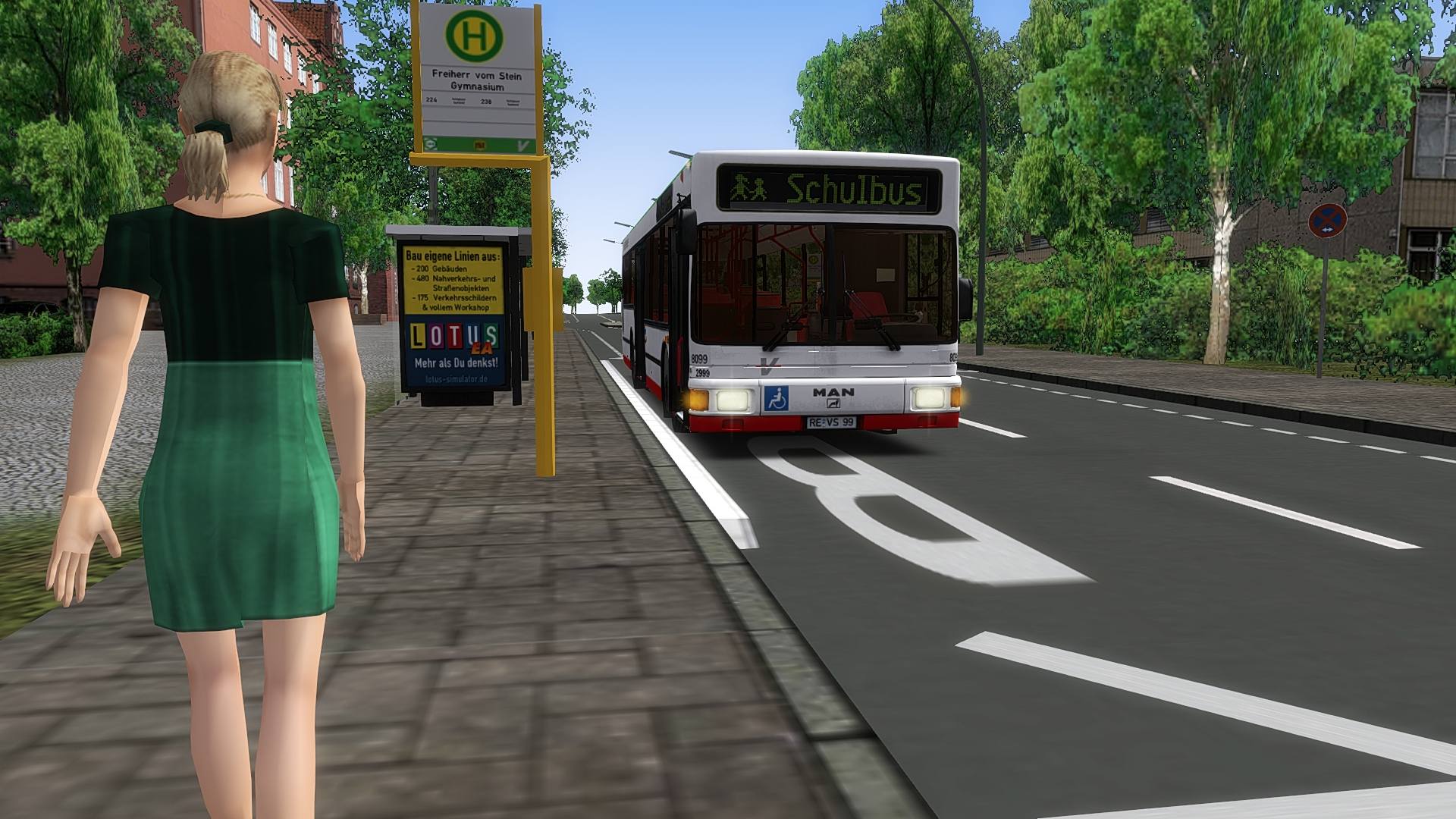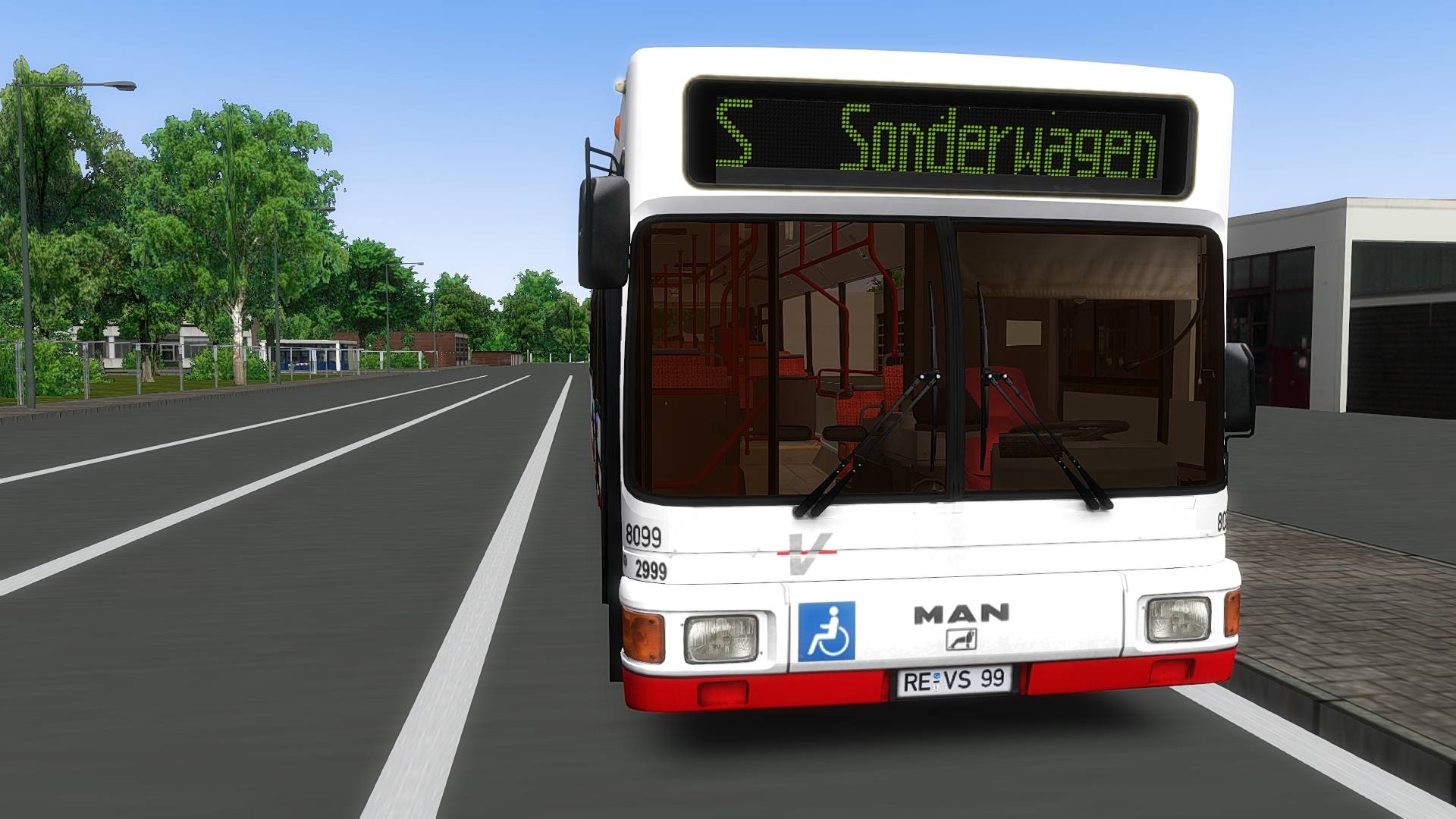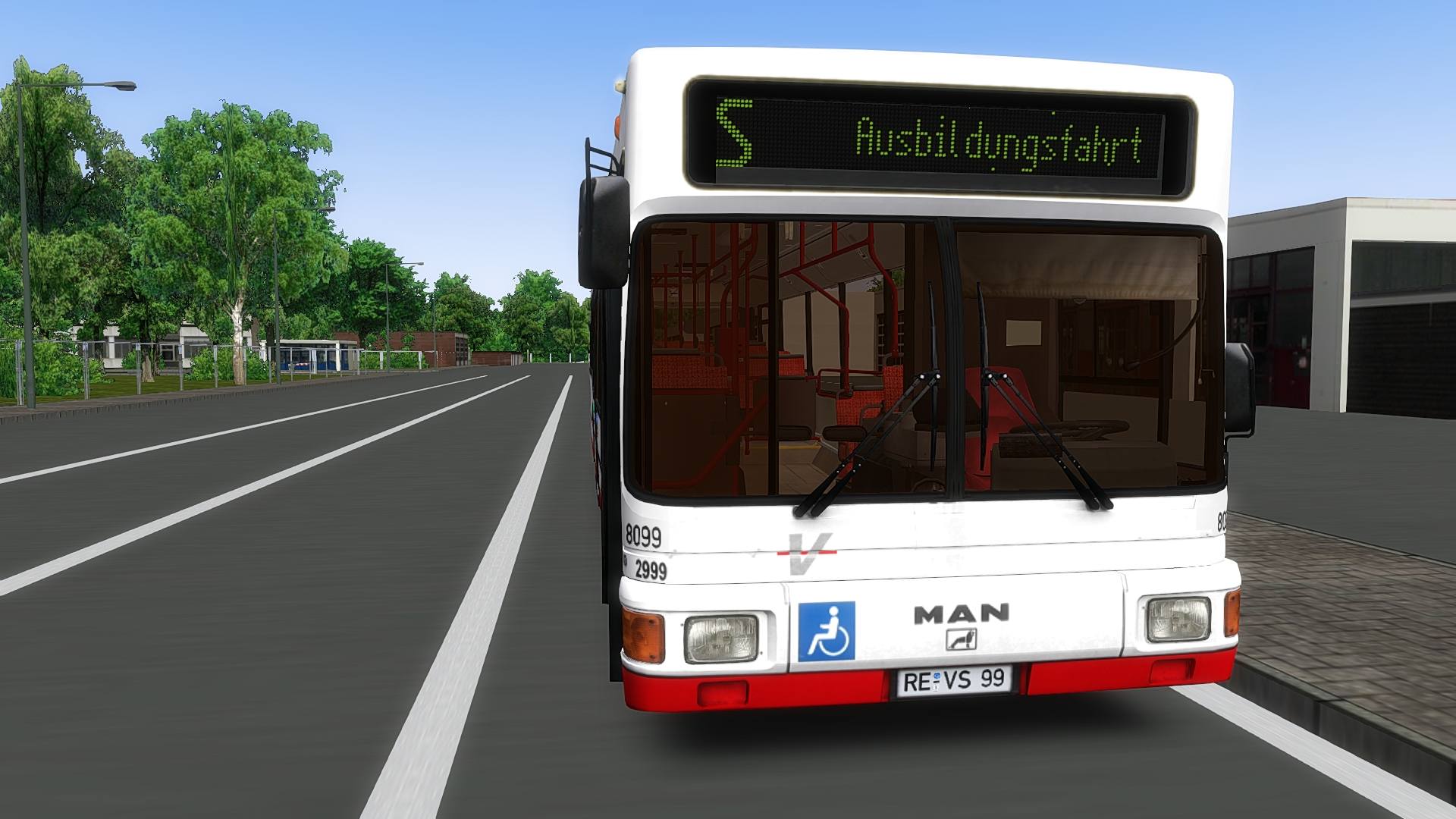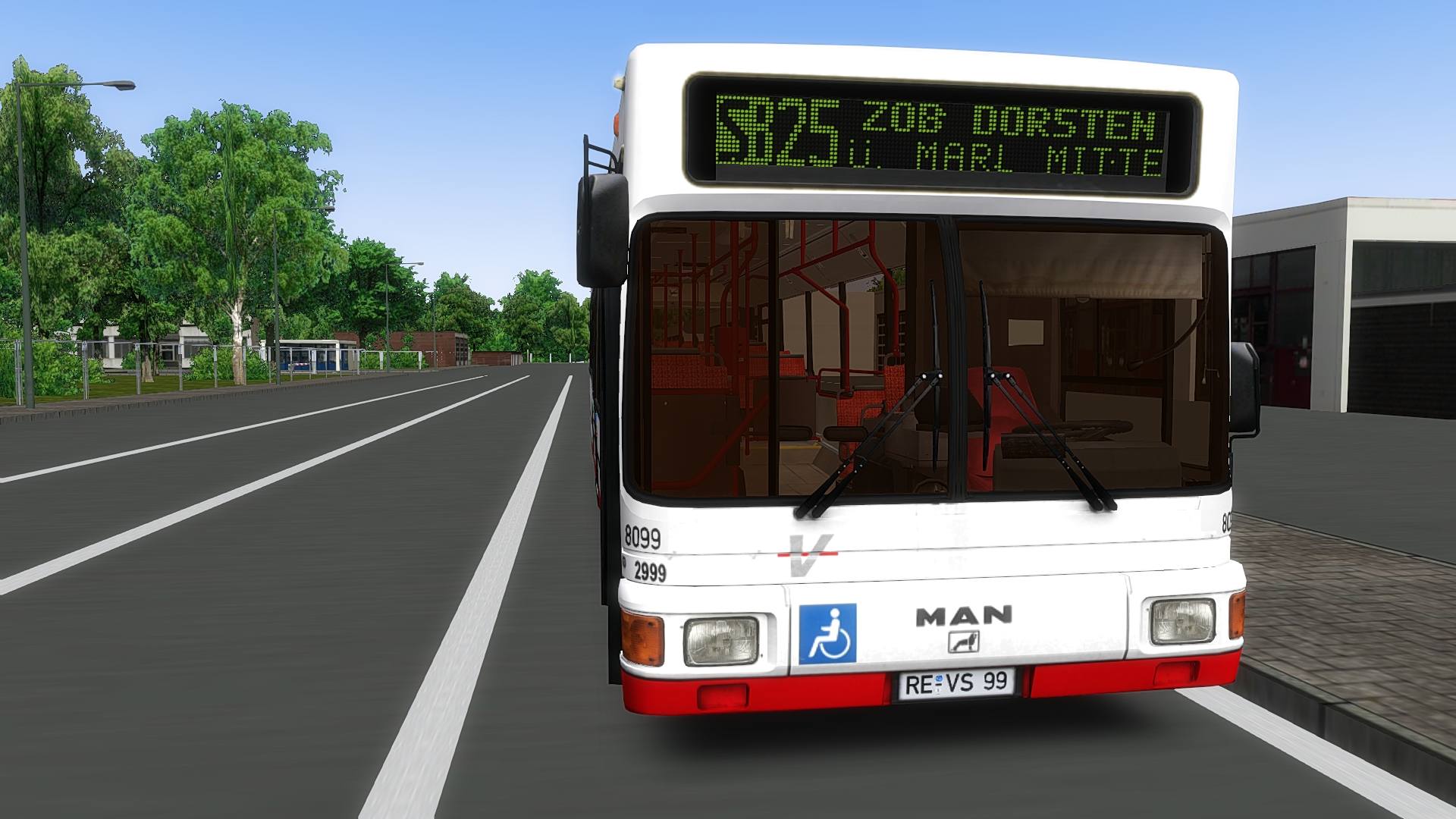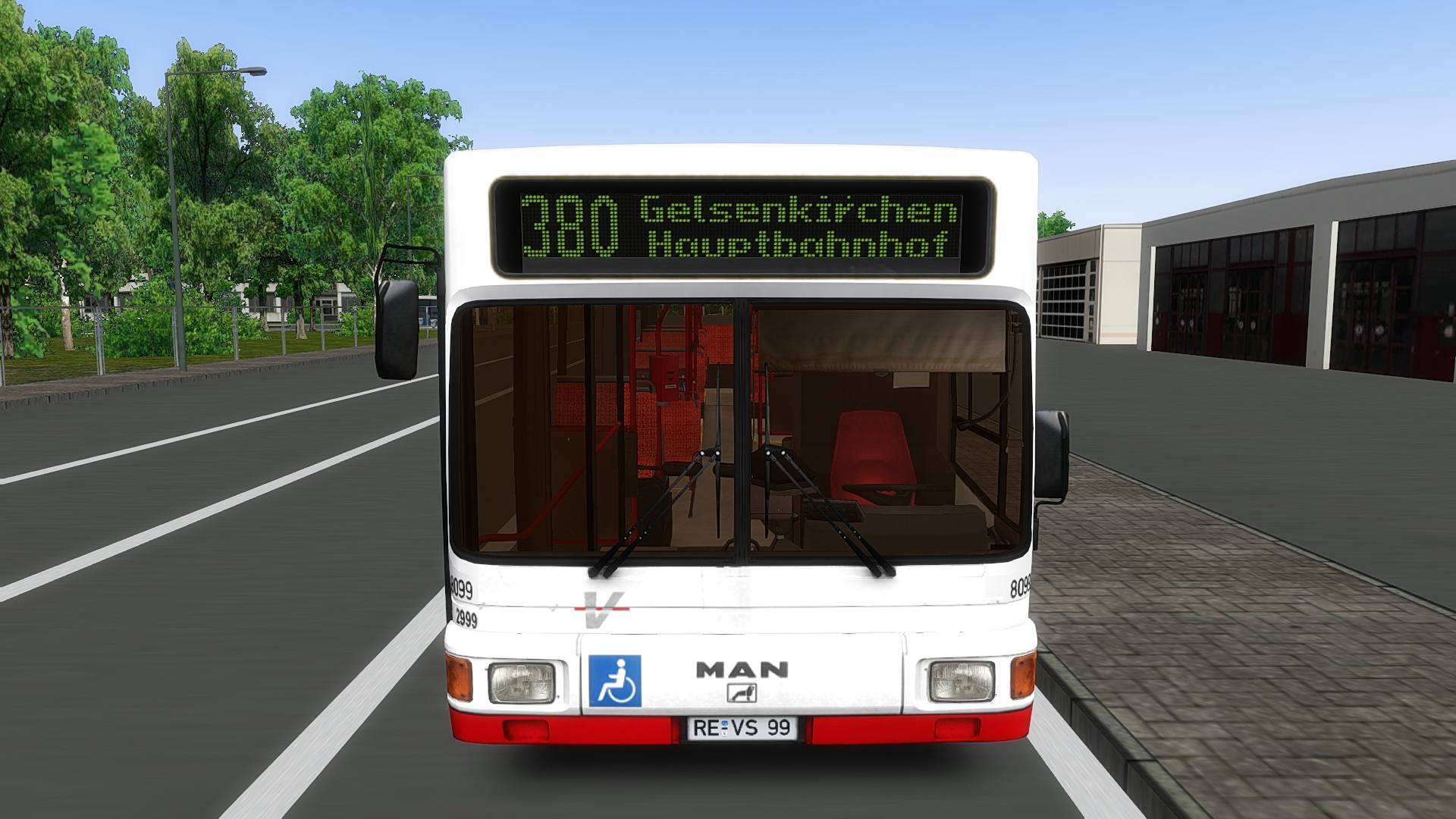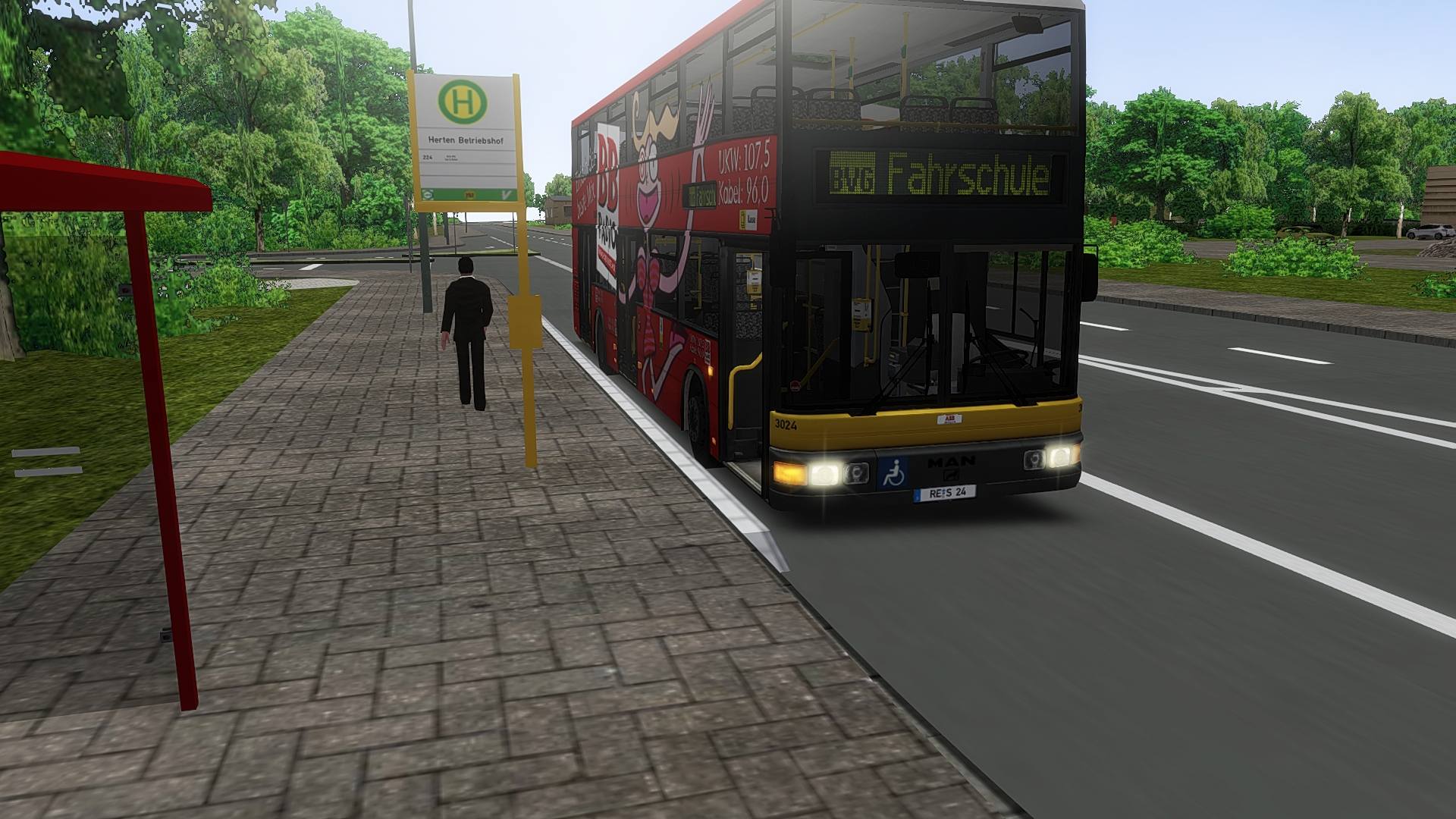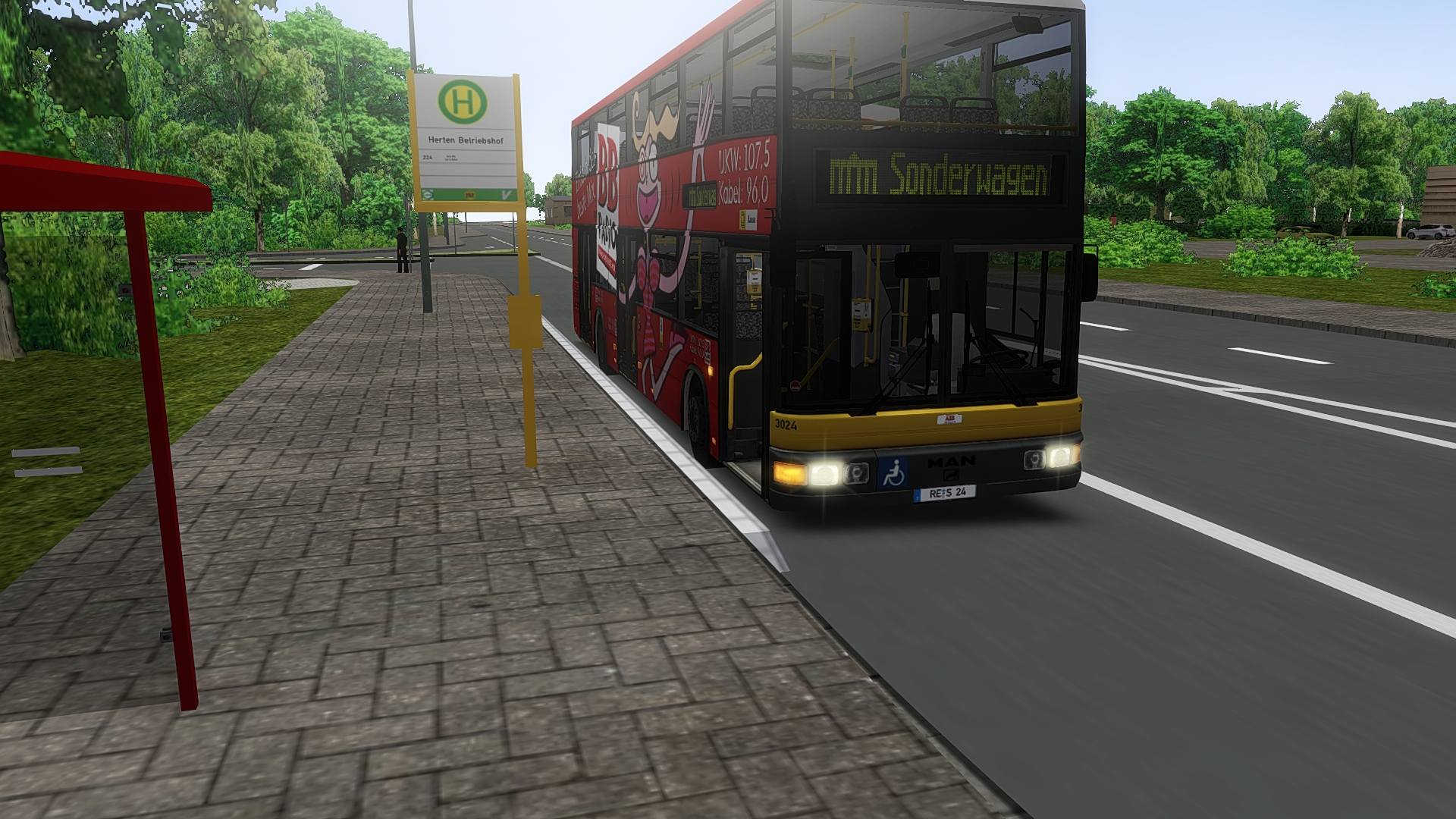
<DE> Mit diesem Mod wird das Groß-/Kleinschreibung sowie weitere Sondersymbole für die Linie bei der Standard KRUEGER Vollmatrix realisiert.
<EN> With this mod the upper/lower case and other special symbols is realized for the linienumber with the standard KRUEGER fullmatrix.
<DE> Folgende Suffix "lE-Telegramm" sind neu oder wurden verändert:
<EN> the following suffixes "lE-Telegram" are new or have been changed:
<DE> Fast vergessen: Ich habe auch S und U Symbole realisiert für Ziele. Folgende Buchstabe muss dann im Hof-Datei im Zieltext eingefügt werden:
<EN> Almost forgotten: I also realized S and U symbols for goals. The following letter must then be inserted in the courtyard file in the target text:
S-Symbol = ì
U-Symbol = î